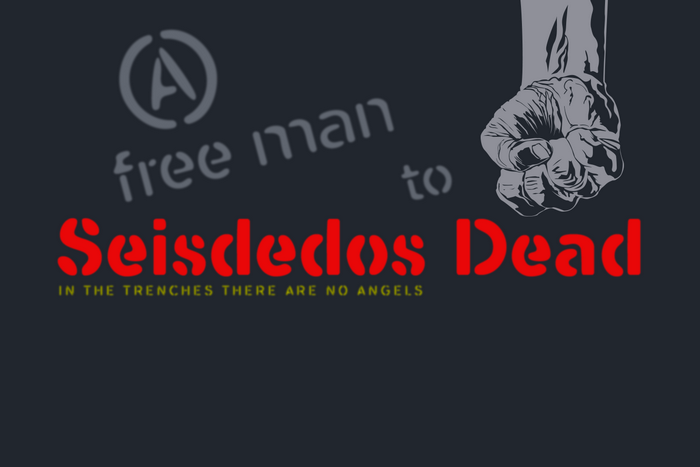
A fonte ‘Seisdedos Dead Fonts’ é uma criação interessante para designers amadores e profissionais que buscam adicionar um toque único a seus projetos. Seisdedos Dead são duas linhas do tipo stencil, regular e bold, que foram sujeitas ao processo de erosão por uso. Isso resulta em uma jogada tipográfica divertida para a desconstrução dos caracteres originais, criando um estilo de impressão antigo onde os anos passados são apreciados. As tipografias se originam das fontes “Flamante Stencil”. O uso do Bitcoin símbolo b# adiciona uma nova dimensão ao projeto. Esta fonte é perfeita para criar ambientes que valorizam a memória e o tempo, proporcionando um gosto de nostalgia aos seus projetos. A Fonte ‘Seisdedos Dead Fonts’ está disponível em versões completas com licença comercial para quem deseja incorporar essa rara combinação de estilo antigo e moderno nos seus trabalhos. Essa fonte é uma ótima escolha para designers que buscam estilos distintos, interessantes e únicos para projetos variados, como cartazes, design gráfico ou até mesmo para criar um estilo próprio em designs pessoais.